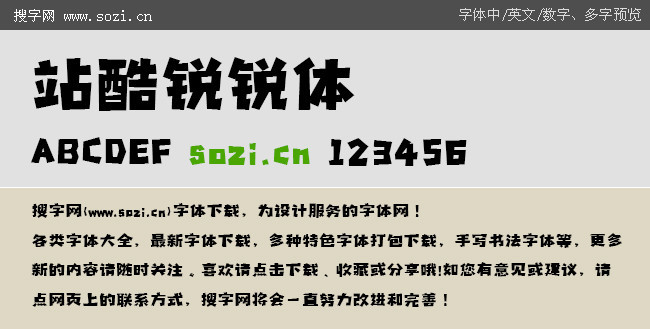
站酷銳銳體
搜字網(wǎng)提供一款站酷銳銳體中文字體下載,站酷銳銳體是由劉兵克設(shè)計工作室打造的全新字體,該字體字形飽滿豐盈,卡通可愛,充滿稚氣感和童真氣息,不規(guī)則四邊形的筆畫組合,使得字體靈活多變,趣味十足;適用于海報設(shè)計、兒童包裝設(shè)計,網(wǎng)頁設(shè)計等廣告應(yīng)用。(此款為個人非商用版,如需商用請聯(lián)系作者購買)